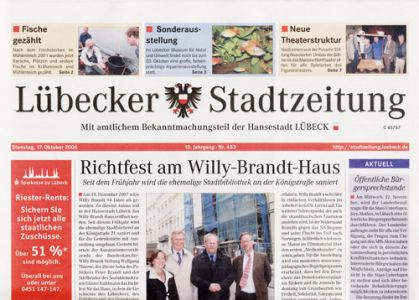
frage zur corporate!
da hätte ich gleich mal eine erste frage!
ich beschäftige mich gerade für die schule mit der Corporate a-s-e von Kurt Weidemann. Leider finde ich, außer von Mercedes natürlich, keine Beispiele, wo diese Schrift sonst noch verwendet wird.
kann mir da jemand weiterhelfen??
Die Lübecker Agentur MIKADO hatte seinerzeit, das war aber leider vor meinem Eintritt, das gesamte CD der Hansestadt Lübeck in Zusammenarbeit mit Prof. Weidemann auf die Corporate-Familie umgestrickt, mit Ausnahme der E (Egyptienne). Das war die Grundlage für das gesamte öffentliche Erscheinungsbild Lübecks, vom Behördenformular bis zum Plakat. Auch erscheint neben den Lübecker Nachrichten eine eigene Zeitung der Bürgerschaft, die „Lübecker Stadtzeitung“, komplett in der Corporate gesetzt. Auch das Wappen wurde unter heraldischen Gesichtspunkten neu entworfen, in diversen Varianten. Hier mal ein Scan der Stadtzzeitung, darunter der Hauptprospekt von 1996.
noch eine frage - kann es sein, dass die corporate auch im kabel-1 logo drinnen ist? also, nicht im logo sondern im text darunter? (kabel1.de)
nein, das ist die ff din.